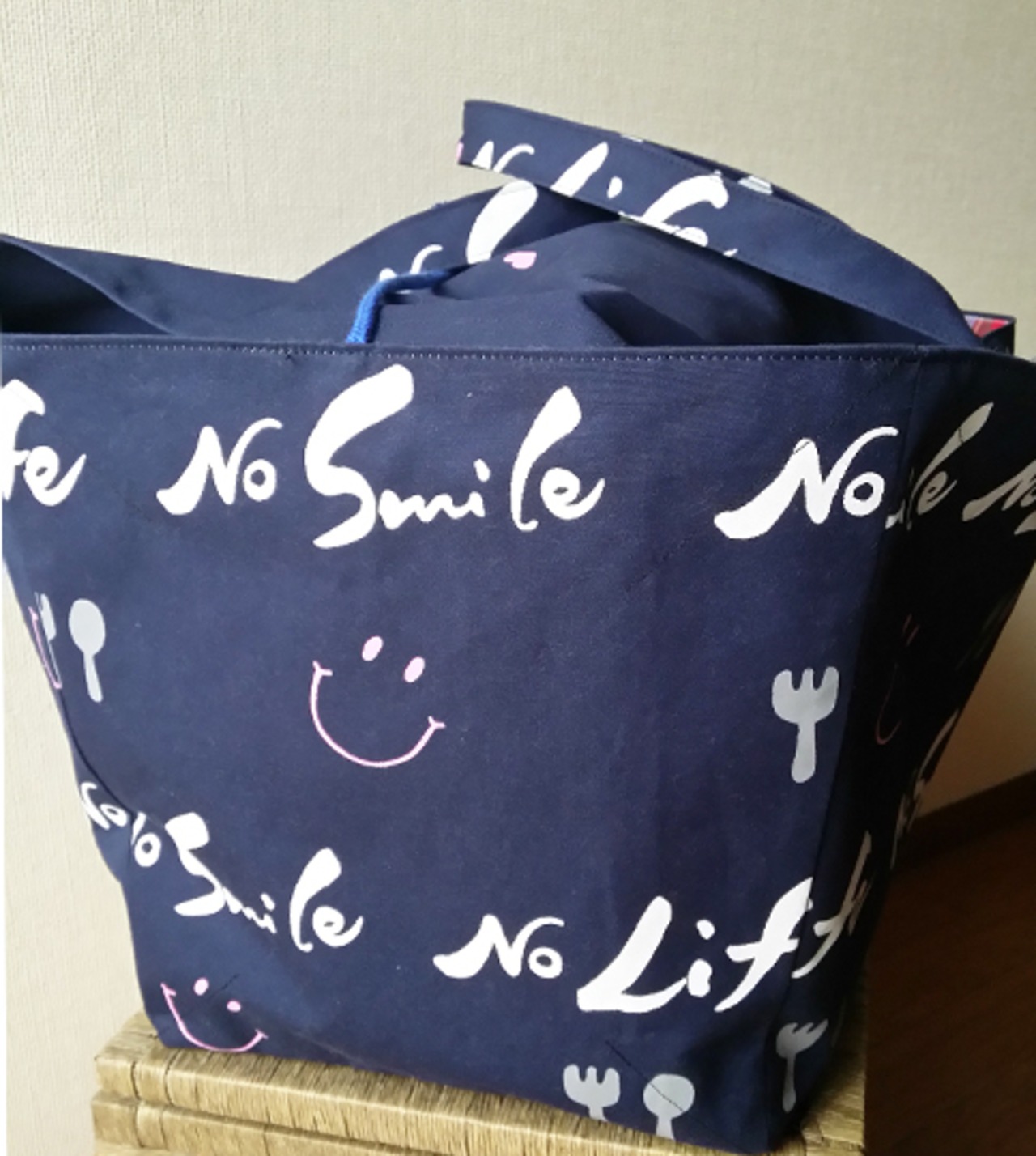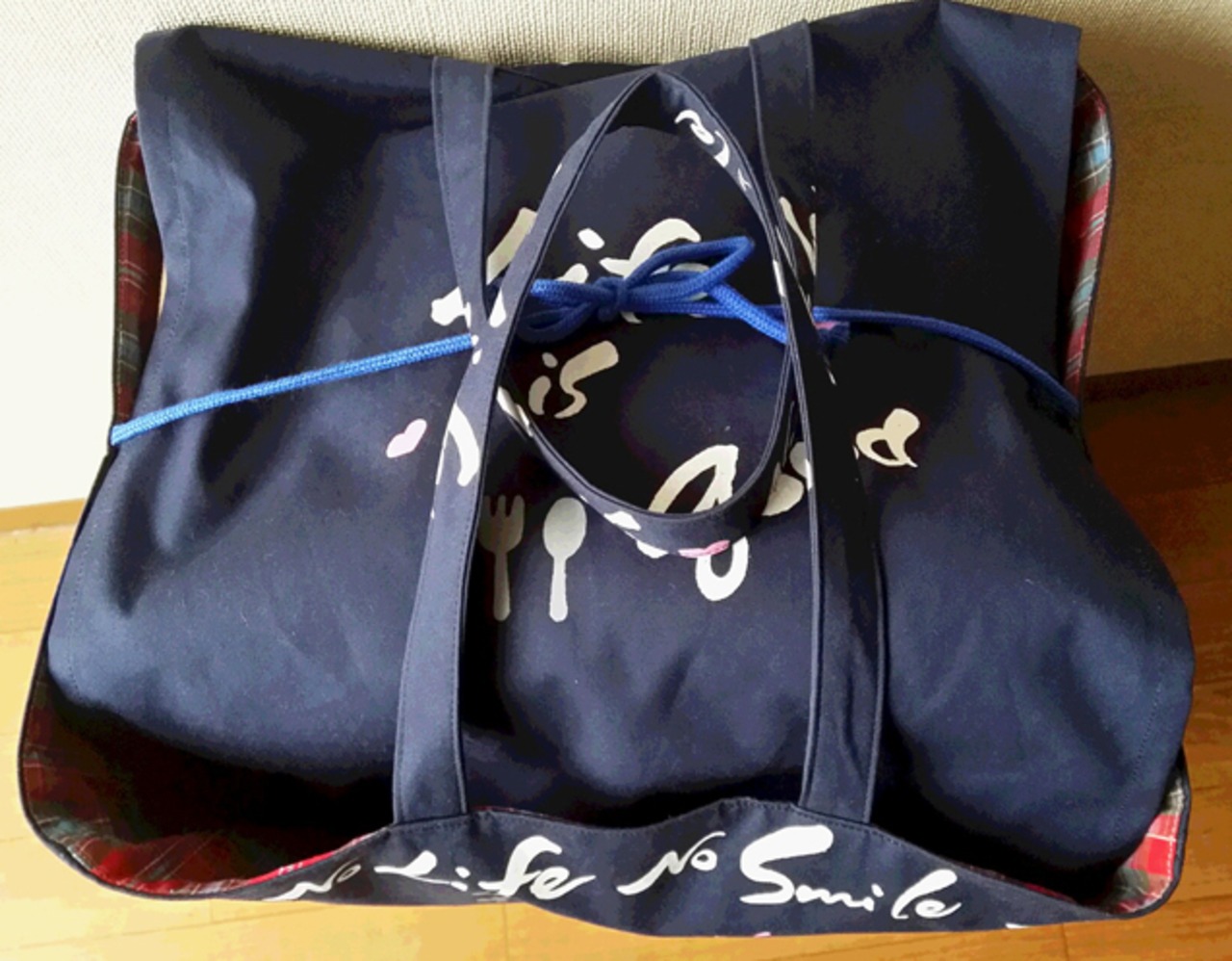
SmileレジかごバックNo11☆
Smileレジかごバック第11弾出来ました~♪
ネイビーが初登場です!!
ロゴも新しくなりましたよ~~( *´艸`)
お買い物バックもこだわってオシャレに!!
綿100%の生地に筆文字デザインを印刷した完全オリジナルです。
今回はPOPなCafe風にデザインしてみましたよ~♡
毎日の買い物がウキウキになっちゃうかも・・・